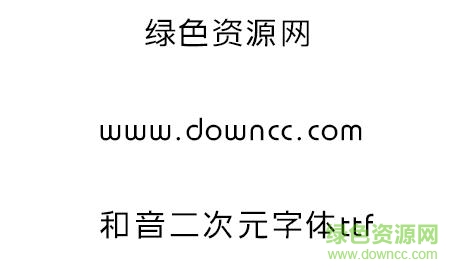
和音二次元字體ttf是一款混搭二次元字體,這款字體將二次元字體進(jìn)行了縮小,同時混搭了其他的字體效果,讓你感覺到更加不錯的使用體驗(yàn),這款字體在二次元界廣為流傳,受到萬千二次元小伙伴喜愛,快來綠色資源網(wǎng)下載吧!
這款字體的最大特色在于能夠帶給喜愛字體的用戶們韓很舒適的視覺享受,這款字體在規(guī)整中帶著圓潤,同時漢字與英文表現(xiàn)效果又大有不同,十分好看!